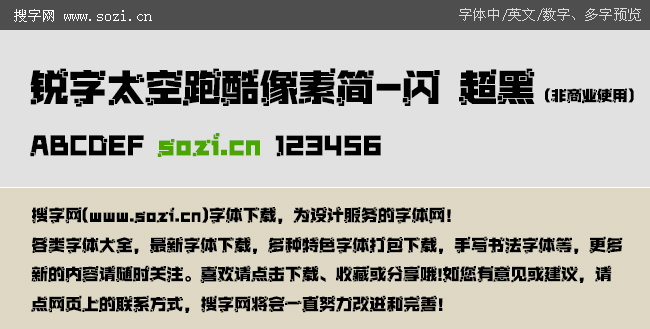
锐字太空跑酷像素简-闪 超黑
搜字网提供一款锐字太空跑酷像素简-闪 超黑中文字体下载,锐字太空跑酷像素简-闪 超黑是一款像素体艺术字体,字型饱满方正,部分笔画转折处的内部根据空间加入直角像素特点,并在笔画上增加横线与小方块的元素、对角分布均匀适当,使字体更具视觉效果。适合用于标题设计、海报设计、包装设计等场景广泛应用。(本字体为个人非商用版,商用请联系作者购买授权。官方网址:http://www.reeji.com 联系方式:021-58597892)